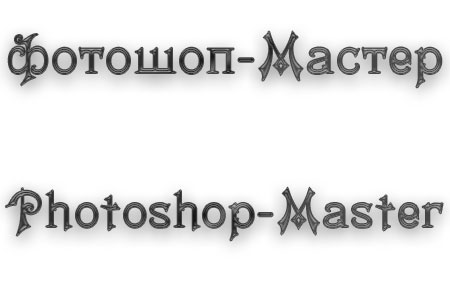
Дополнения Шрифты Татьяна Гапонова 25 апреля 2009 Шрифт - Matilda Красивый шрифт для работы в Фотошоп с поддержкой русского языка. Скачать Шрифт - Matilda